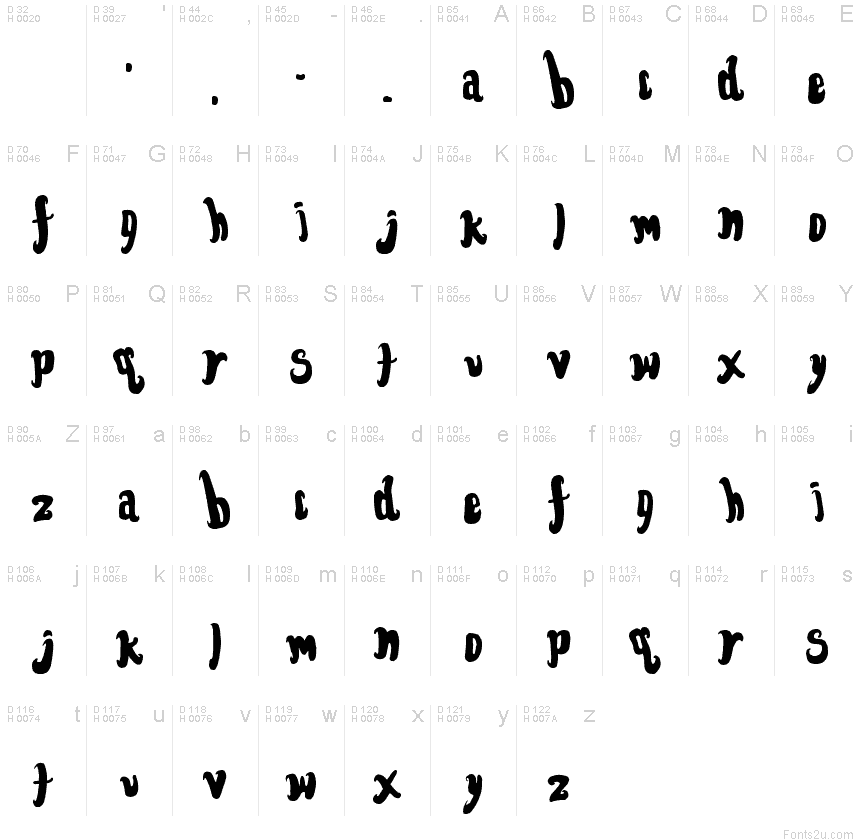
Font For The Dumped autorstwa Jasona Fagone to darmowy krój pisma typu display, wyglądający jakby został nabazgrany grubym, nasyconym tuszem markerem o drugiej nad ranem. Jego pętelkowate, niemal wywrócone na drugą stronę krzywizny i masywne pociągnięcia aż kipią charakterem, nadając każdemu słowu lekko szaloną energię listu zrywającego z kimś relację. Litery wyglądają na niedoskonałe i odręczne, dzięki czemu Twój tekst staje się surowy, głośny i niepodrabialnie ludzki.
Dzięki Font For The Dumped krótkie hasła uderzają z pełną mocą i zapadają w pamięć, szczególnie w dużych formatach na plakatach, zinach, ulotkach koncertowych, wlepkach czy okładkach płyt DIY. Ten darmowy font sprawdzi się też w odważnych grafikach social media, na transparentach protestacyjnych czy buntowniczym merchu, gdzie chcesz krzyczeć, a nie szeptać. Połącz go z czystym, wąskim bezszeryfowym krojem w tekście głównym, aby okiełznać tę dzikość, podczas gdy nagłówki będą robić zamieszanie.